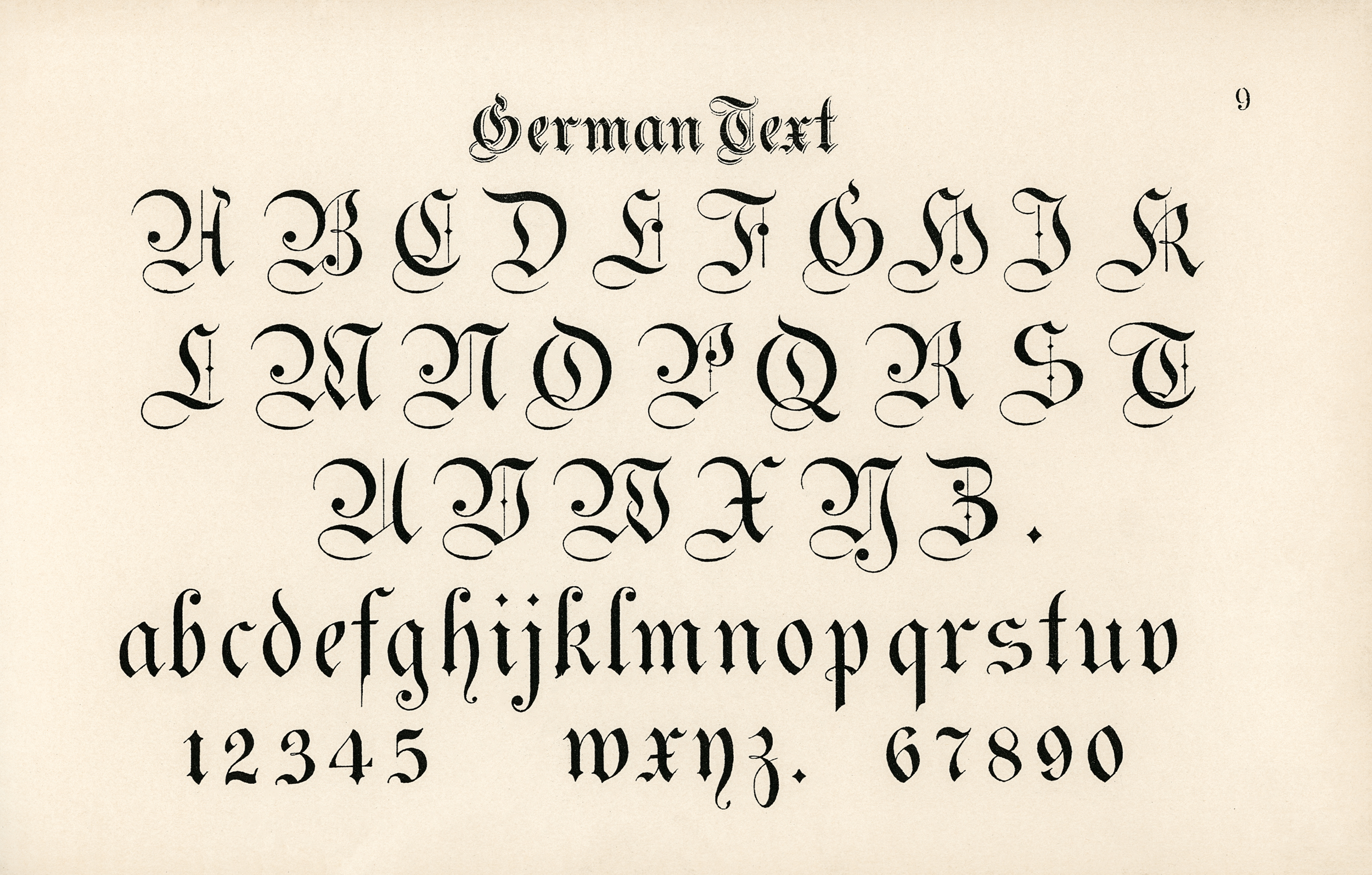
Секреты алфавита
Немецкий язык считается официальным в Австрии, Лихтенштейне и, разумеется, Германии. Помимо того, это один из официальных языков в Бельгии, Швейцарии и Люксембурге. Так вот, если вы собрались в туры по странам, то любой туроператор по Германии скажет, что необходимо выучить хотя бы основы немецкого языка. Что касается происхождения, то немецкий язык можно отнести к индоевропейской группе, одноименная ветвь. Письмо ведется на основе латинского алфавита.
Немецкий алфавит состоит из 26 пар букв латиницы (прописные и строчные), есть лигатура эсцет, умляутированные буквы ä, ö, ü, но в основу алфавита они не входят. Когда происходит алфавитная сортировка, умляутированные буквы ä, ö, ü не отличаются от a, o, u. Исключение составляют лишь слова, которые различаются лишь умляутом, в данном случае такое слово идет позже. Эсцет ß был приравнен к сочетанию ss.
Из опыта туроператоров по Германии: секреты языка
До 20 столетия на официальной основе использовался готический шрифт, к примеру, был введен и особый рукописный готический шрифт. В более приемлемом для европейцев сочетании буквы стали использоваться неофициально с 19 столетия, а вот после того, как Ноябрьская революция 1918 года увенчалась успехом, шрифт был введен официально. Нацисты в свое время пытались вернуть готическое написание, но успехом их попытки не увенчались, современные немцы используют подобное написание разве что в декоративных целях.
Немало условностей существует и в произношении немецких имен. В русском языке выработана довольно простая традиционная система, но многие условия произношения в нее не вошли. Исходной формой транскрибирования считается именительный падеж, причем артикль возле названия ставится, если это имя собственное или это название не употребляется без этой частицы.
История и происхождение немецкого языка, характерные черты немецкого языка
История немецкого языка
Немецкий язык (Deutsch, Deutsche Sprache) — это язык немцев, австрийцев и части швейцарцев. Он является официальным языком Германии, Австрии, Лихтенштейна, одним из официальных языков Швейцарии, Люксембурга и Бельгии.
Немецкий язык относится к индоевропейской семье языков (германская ветвь). Письменность — на основе латинского алфавита.
До начала XX в. официально использовался готический шрифт (в частности, существовал особый готический рукописный шрифт). Буквы в общепринятом европейском начертании используются сначала неофициально с XIX в., а после победы Ноябрьской революции 1918 г. вводятся официально. Попытки нацистов вернуть готический шрифт в качестве официального успеха не имели, и в настоящее время он используется лишь в декоративных целях.
Немецкие имена и названия передаются в русском языке по традиционной системе, достаточно простой, но в то же время часто условной и произношения не отражающей.
Литературный немецкий язык (Hochdeutsche Sprache, или Hochdeutsch) развился на основе верхне(южно)немецких и средненемецких диалектов, в которых в течение средних веков произошло так называемое второе передвижение согласных. Постепенно он также оказывал влияние на диалекты, не подвергшиеся второму передвижению согласных, — нижне(северо)немецкий язык (Niederdeutsch).![]()
Слово «teutsch» (Deutsch) является латинским новообразованием на основе германского слова «народ» (thioda, thiodisk) — оно обозначало язык народа, который не разговаривал на латыни.
Первая попытка к объединению наречий была предпринята примерно около 1200 года в средненемецкой поэзии. Успехи этой попытки заметны, так как поэты, желая быть понятыми и за пределами своих регионов, старались избегать региональных слов и выражений. Но не стоит придавать этой попытке особо большого значения, т. к. большинство населения было неграмотным. Поэтому учёные считают, что развитие нового письменного и устного Hochdeutsch произошло в период позднего Средневековья и в раннем Новом времени (Frühe Neuzeit).
В большинстве европейских стран стандартный литературный язык опирается на диалект столицы этой страны. Немецкий стандартный язык (Hochdeutsch), в отличие от практики большинства европейских стран, представляет собой нечто среднее между средненемецкими и верхненемецкими диалектами.
В северной части Германии стандартный немецкий язык (Hochdeutsch) распространился как язык государственного управления и школьного образования во время Реформации. В эпоху расцвета Ганзы по всей северной Германии царили нижненемецкие диалекты и нидерландский язык. Со временем литературный немецкий в северных регионах Германии практически заменил местные диалекты. А так как нижненемецкий диалект очень отличается от литературного, образование какого-либо компромиссного говора было невозможно, и большинство современных жителей северной Германии говорят только на литературном немецком и даже зачастую уже не владеют диалектом предков. В центре и на юге Германии, где язык изначально был более похож на литературный, население сохранило свои диалекты.
Мартин Лютер перевёл в 1521 году Новый Завет и в 1534 Ветхий Завет на тогда ещё не устоявшийся стандартный новонемецкий письменный язык (Neuhochdeutsch).
Со временем вся печатная продукция должна быть переведена на этот стандартный шрифт. Это произойдет как можно скорее в отношении школьных учебников, в сельских и начальных школах будет преподаваться только стандартная графика.Использование властями швабахерско-еврейских букв в будущем прекратится. Удостоверения о назначении должностных лиц, уличные знаки и тому подобное в будущем будут изготавливаться только стандартным шрифтом…»